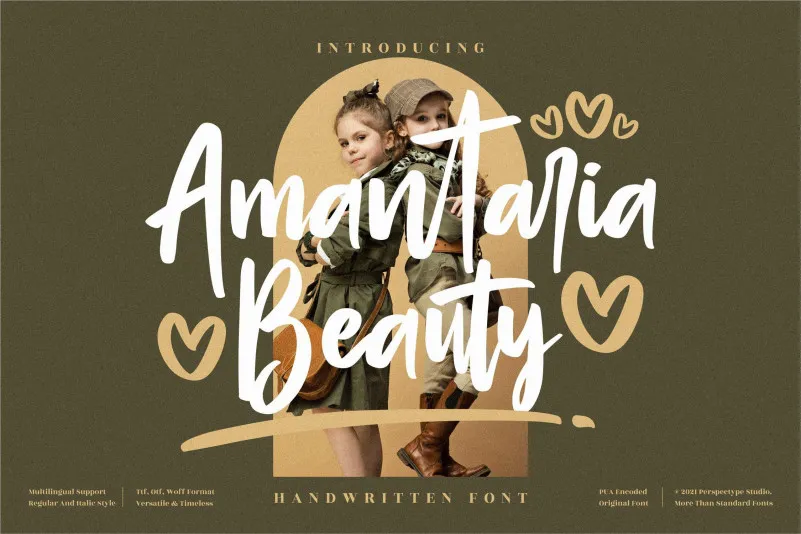
A Amantaria Beauty Font é uma elegante fonte script que oferece uma combinação perfeita de sofisticação e naturalidade. Com seu estilo moderno e pintura branca, a fonte é ideal para adicionar um toque único aos seus projetos gráficos, seja em logotipos, rótulos ou qualquer outra peça de design que exigir uma personalização especial. Ela destaca-se por sua linha suave e variada baseline, garantindo sempre uma aparência atraente e harmoniosa. Além disso, seu conjunto de caracteres exuberantes e alternativas estoniosas oferecem um amplo espectro para criar designs únicos e memoráveis. A Amantaria Beauty é uma escolha perfeita para quem busca uma fonte script que se destaca em qualquer design, proporcionando uma experiência única e envolvente aos seus trabalhos gráficos.